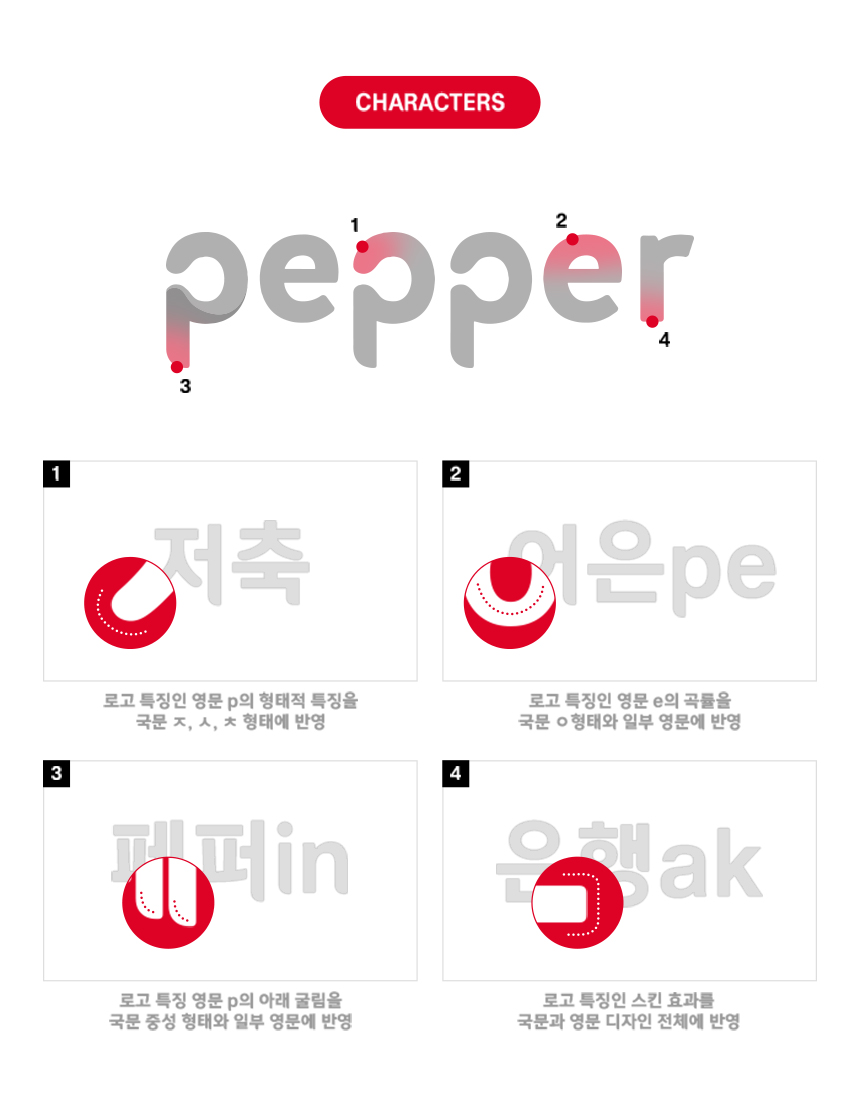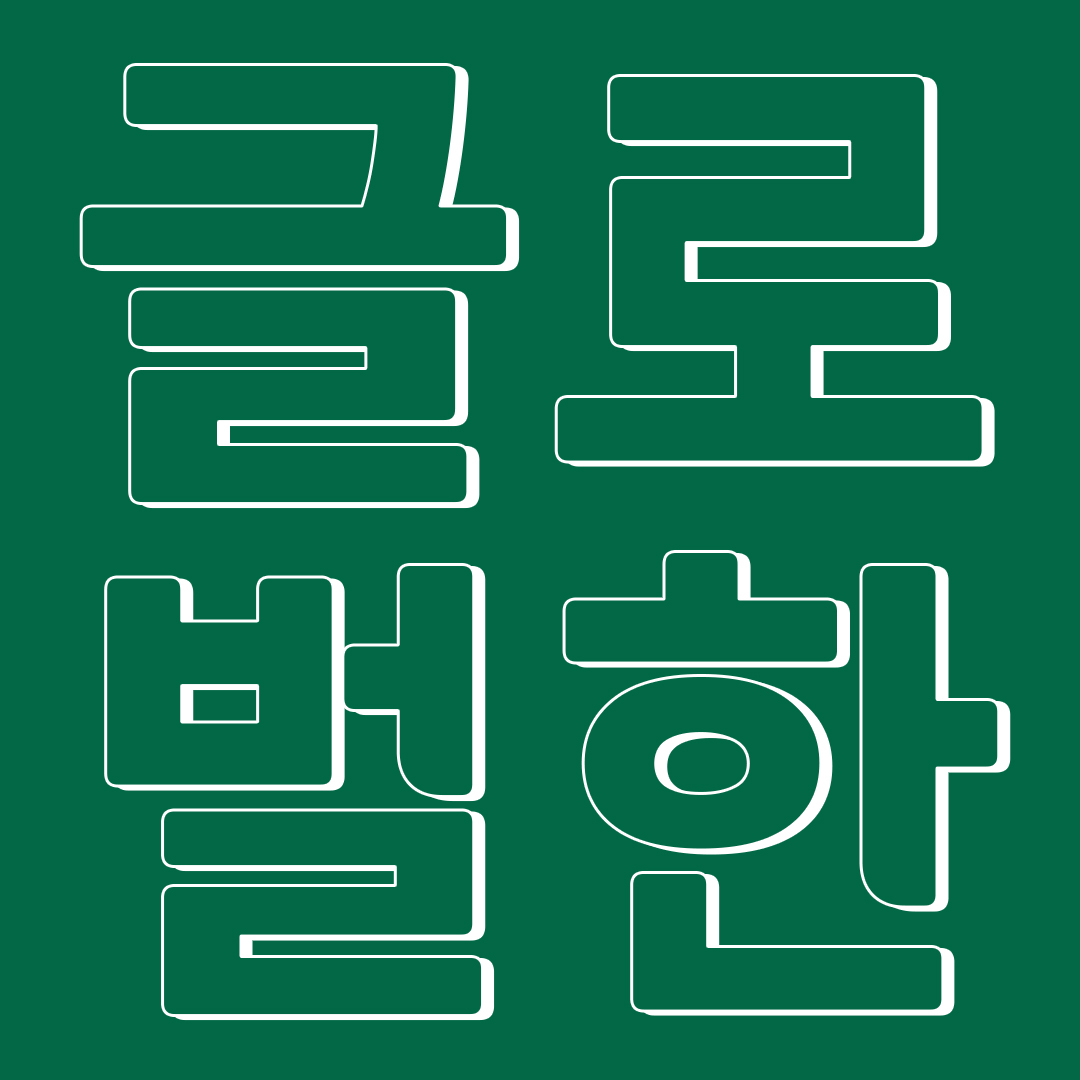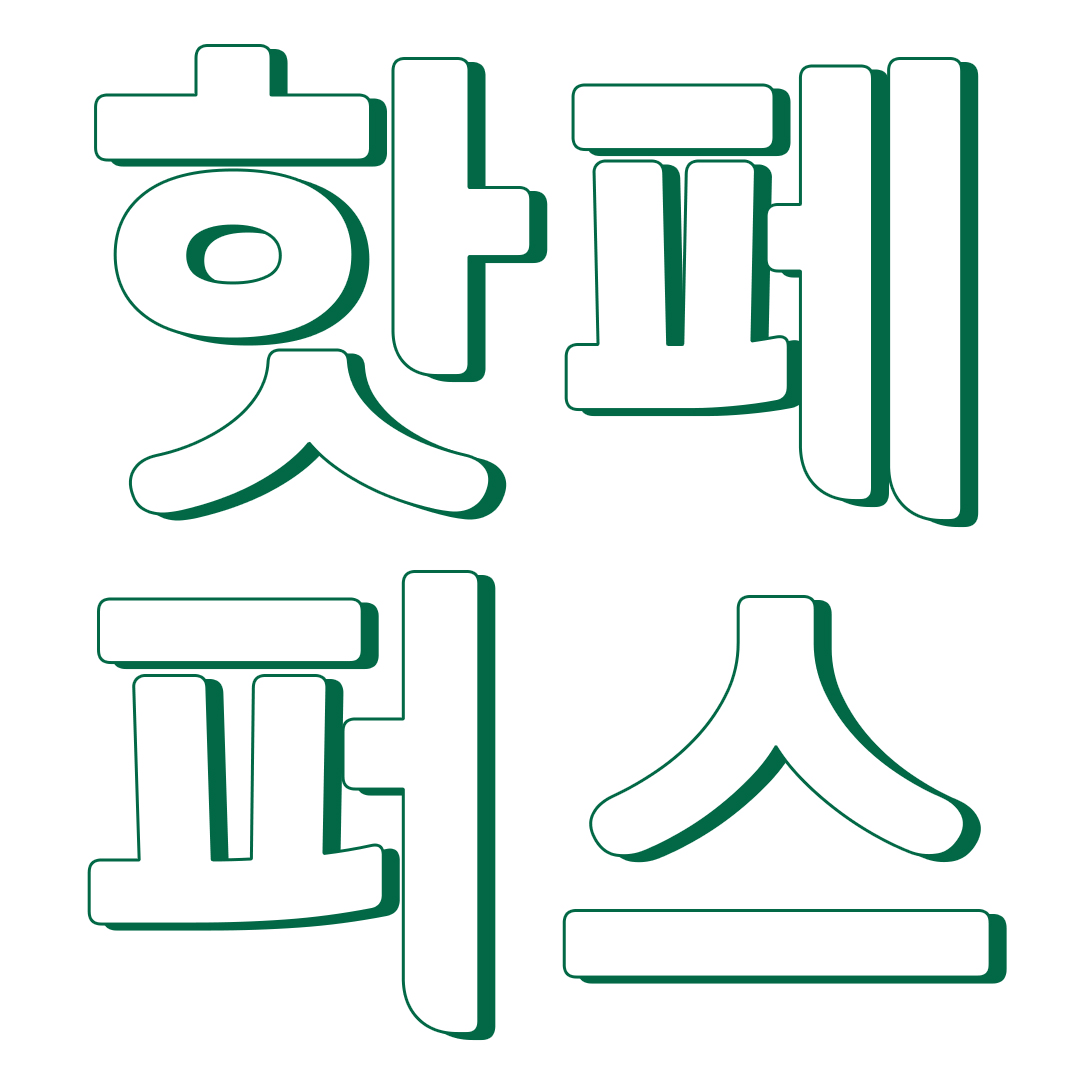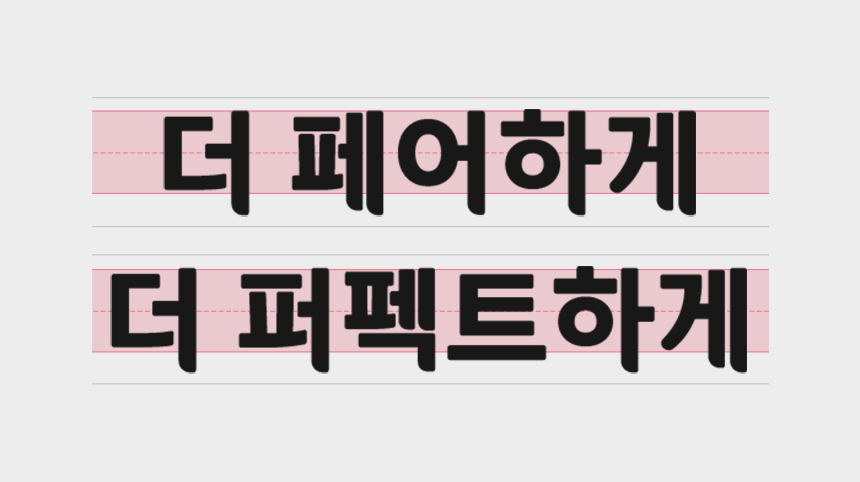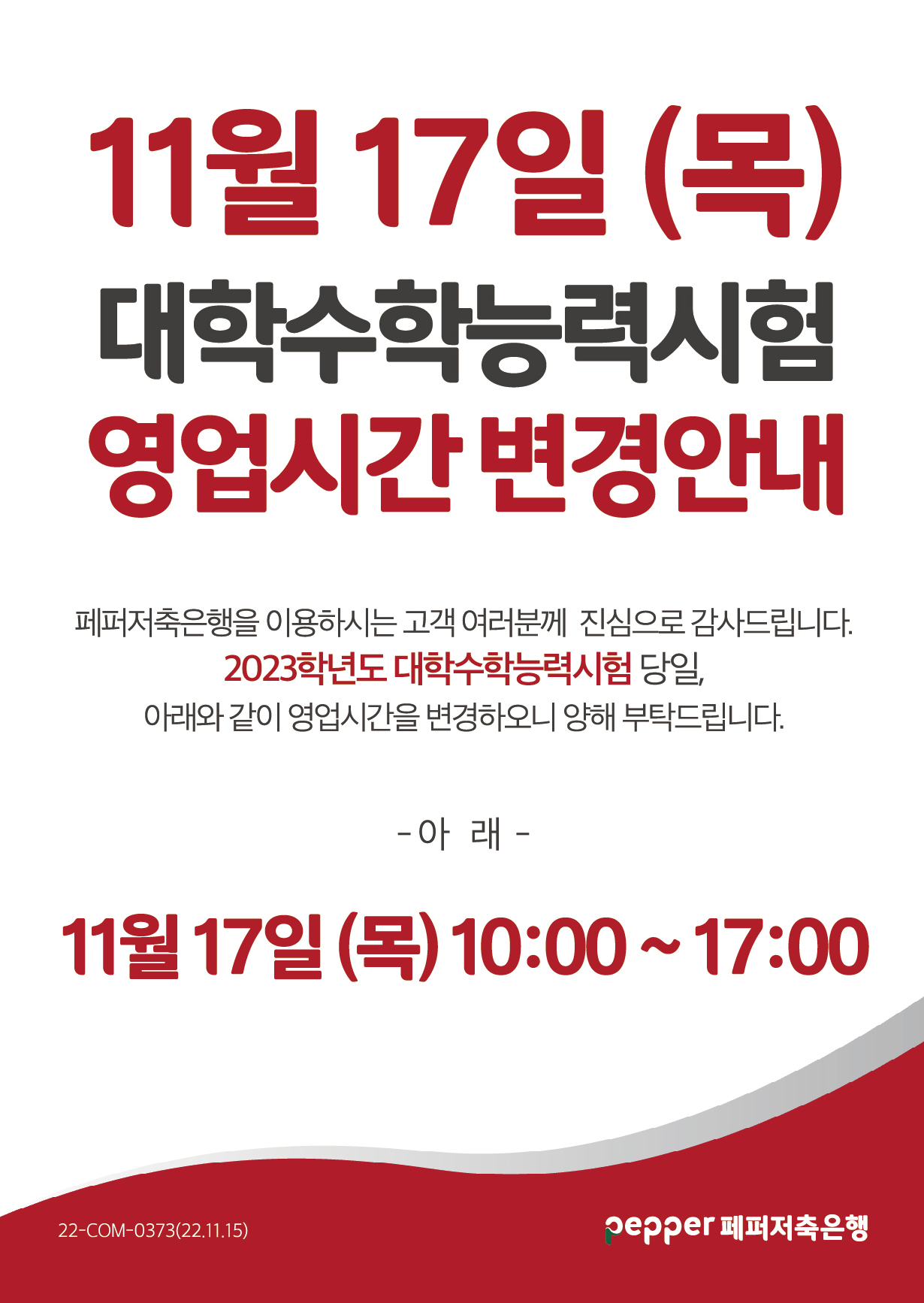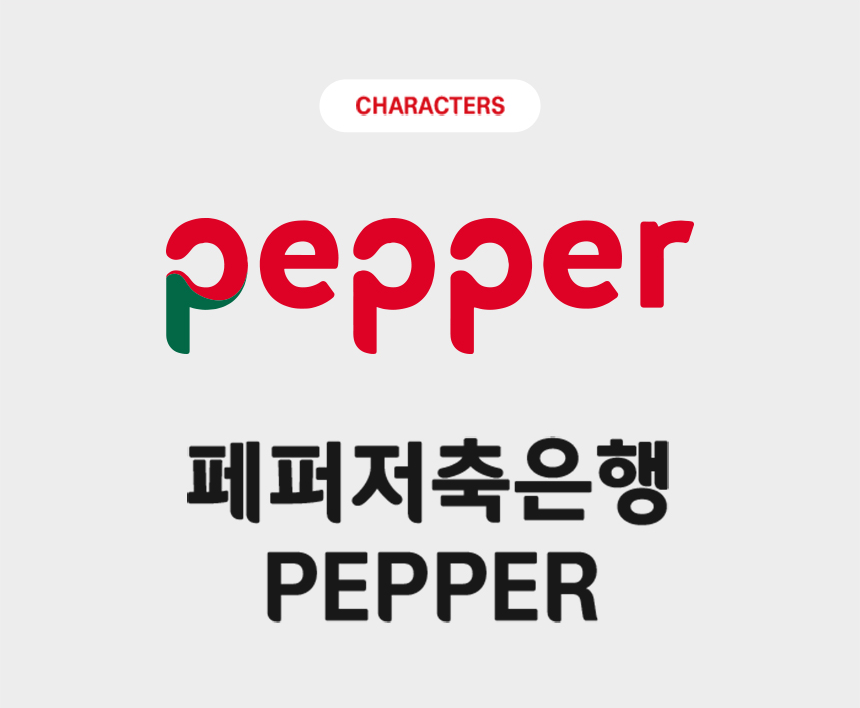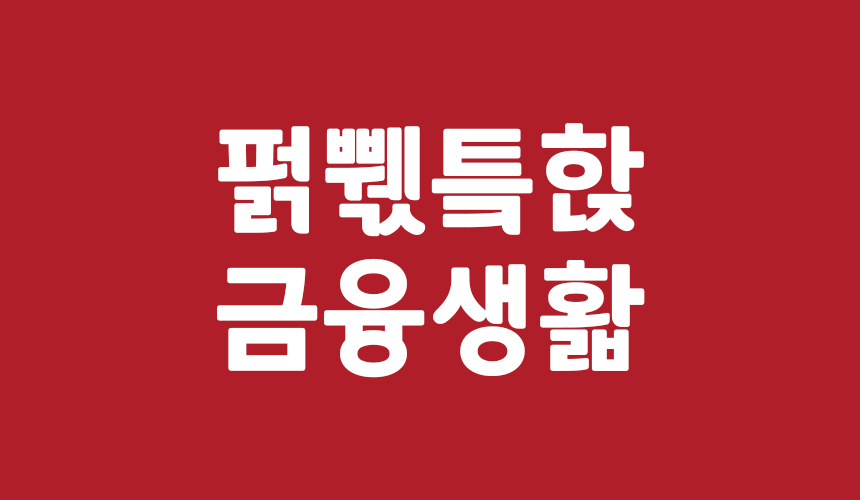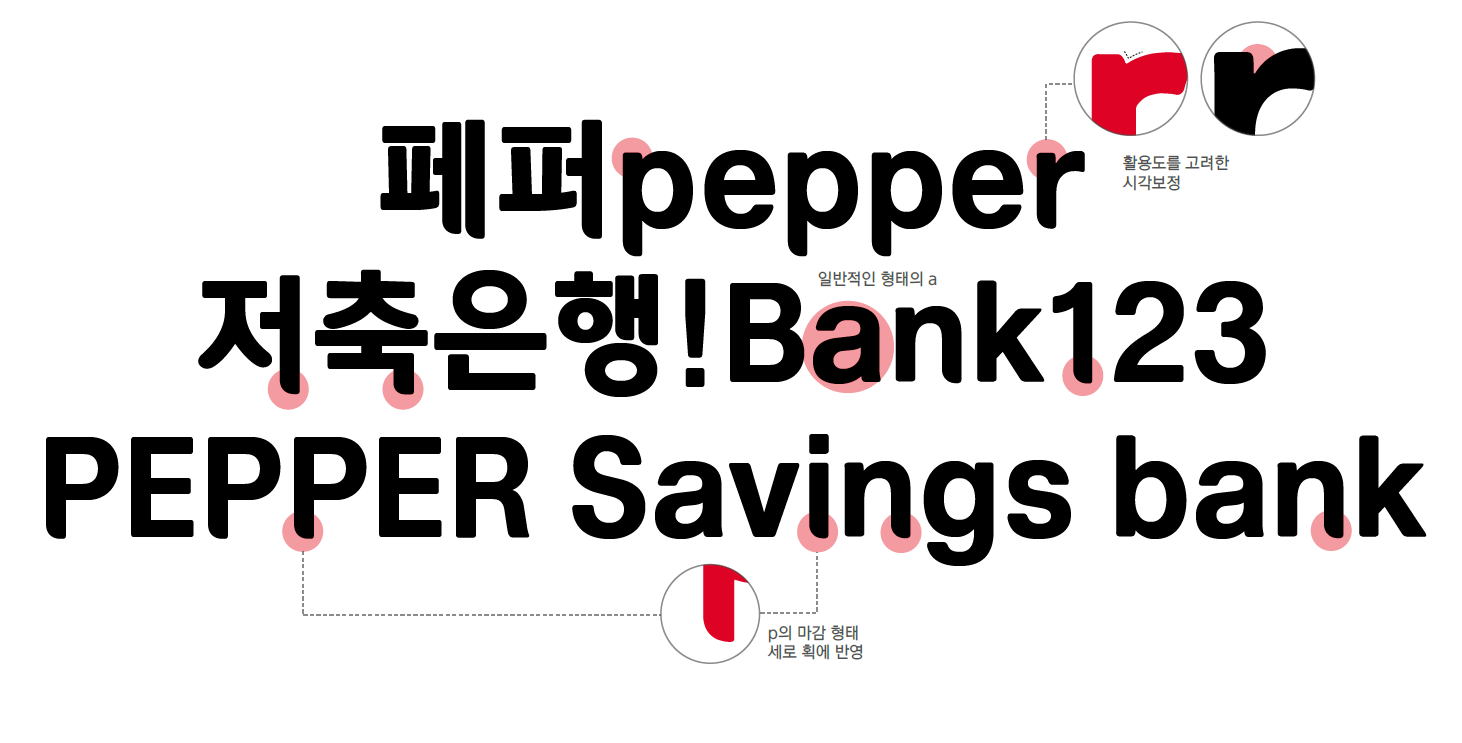
안녕하세요. 오늘은 페퍼저축은행 전용서체 「페퍼스」를 소개해 드리려고 합니다. 글로벌 금융기업 페퍼그룹 CI의 다양한 특징들을 반영하여 통일된 브랜드 이미지를 구축하기 위해 개발된 서체로 다양한 활용성이 기대되는 페퍼스 전용서체에 대해 자세히 알아보겠습니다!
페퍼저축은행 전용서체 페퍼스는 기업의 아이덴티티를 담은 CI를 기반으로 제작한 서체입니다. 페퍼저축은행 CI는 변화하는 디지털 금융 환경에 대응하기 위한 유연함과 따뜻한 서민 금융을 추구하는 페퍼의 브랜드 이미지를 반영하고 있어요.
페퍼그룹의 CI 디자인에서 부드럽고 독창적인 형태 디자인을 볼 수 있는데요, 이러한 혁신적이고 신선한 인상을 전용서체에 그대로 녹이되 동시에 활용성을 높이고자 디자인적인 디테일을 더했습니다.
페퍼저축은행 전용서체는 기존 로고(CI)의 특징을 접목하여 전체적으로 부드럽고 유연한 느낌이 나도록 디자인을 진행했습니다. 글줄 기준선은 중상단으로 조정해 여러 환경에서의 범용성을 높였습니다.
국문과 영문 디자인 전체에 로고의 특징인 둥그런 외곽 굴림 효과와 세로 획의 둥근 깎임을 반영하고, 빗침에 라운드 처리로 부드러운 이미지를 표현했습니다.
영문과 숫자, 기호 등에도 국문에서의 동일한 특징을 반영하여 디자인했습니다. 아이덴티티만 너무 살리다 보면 활용도가 떨어질 수 있는데요, 시각보정이 적용된 일반적인 고딕 형태를 기반으로 제작하여 그러한 부분을 보완했습니다.
페퍼스체는 한글 11,172자로 개발하여 모든 한글 자소를 쓸 수 있어 활용도 높게 제작했습니다.
현재 페퍼스체는 페퍼저축은행 홈페이지와 기업 관련 곳곳에 쓰이고 있습니다. 개인 및 기업 사용자를 포함한 모든 사용자에게 무료로 제공되며 자유롭게 사용할 수 있기 때문에 다양하게 활용해 보면 좋을 것 같습니다🙌